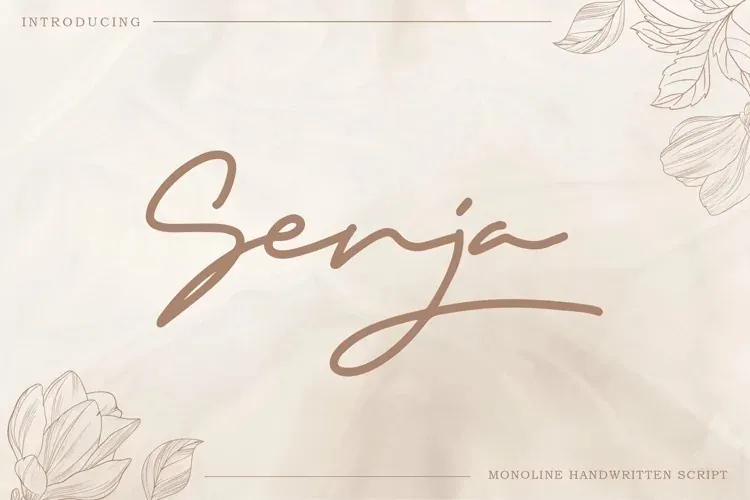
A Senja Font é uma elegante fonte script que transmite autenticidade com sua escrita manuscrita monolínea, perfeitamente adaptada para temas bonitos e modernos. Desenvolvida pelo designer Typefactoryco na categoria de fontes scripts, ela oferece um toque de simplicidade e beleza incomparável. Ideal tanto para assinaturas, cabeçalhos quanto para logos ou produtos de marca, a Senja Font é uma escolha perfeita para projetos que desejam transmitir elegância e criatividade. Seja você um designer gráfico profissional ou iniciante, essa fonte singular vai transformar sua apresentação com sutileza e originalidade.